Schnelle Antwort
Für Instagram Reels funktionieren vor allem klare und gut lesbare Schriftarten wie Montserrat oder Poppins am besten. Wenn du etwas auffälliger sein willst, kannst du fette Schriften wie Impact nutzen, während geschwungene Fonts wie Dancing Script eher für Lifestyle-Inhalte passen. Wichtig ist, dass der Text sofort verständlich ist, auch auf kleinen Handybildschirmen. Zu verspielte oder dünne Schriftarten solltest du vermeiden, da sie oft schwer zu lesen sind.
Warum Schriftarten bei Instagram Reels so wichtig sind
Bei Instagram Reels entscheiden Nutzer oft schon in den ersten 1–2 Sekunden, ob sie weiter schauen oder weiter scrollen. Eine klare und auffällige Schrift kann sofort Aufmerksamkeit ziehen und den Zuschauer stoppen. Gut gewählte Schriftarten machen deinen Text leichter verständlich und sorgen dafür, dass mehr Leute mit deinem Inhalt interagieren. Gleichzeitig helfen sie dir dabei, einen eigenen Stil aufzubauen, sodass deine Reels wiedererkannt werden.
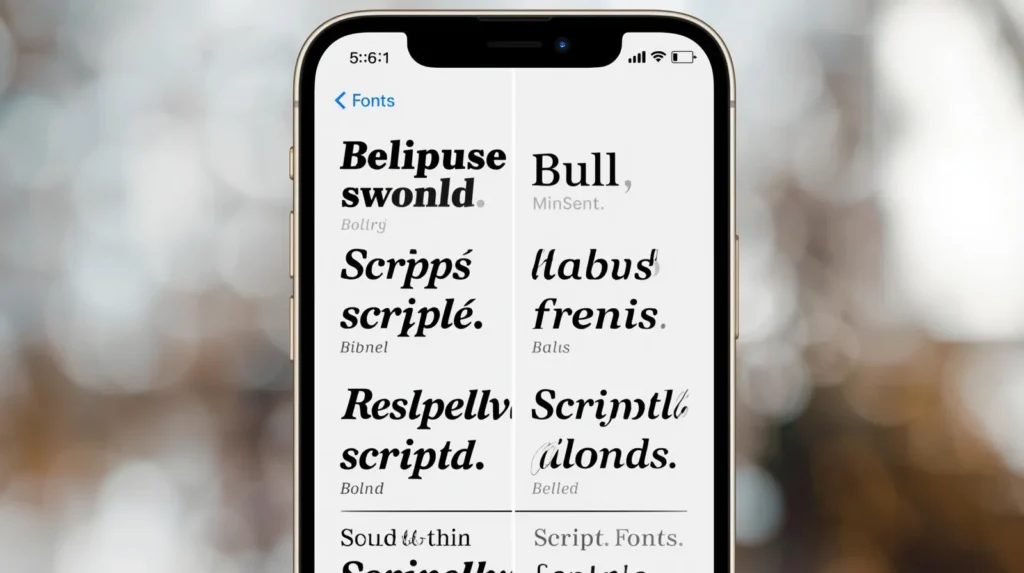
Die besten Schriftarten für Instagram Reels (nach Stil)
Klare & moderne Schriftarten
Montserrat, Helvetica und Poppins sind perfekt, wenn du Texte einfach und schnell verständlich machen willst. Sie eignen sich besonders gut für Business-Inhalte, Hooks und Überschriften, weil sie sauber und professionell wirken.
Elegante & geschwungene Schriftarten
Dancing Script, Pacifico und Allura wirken weicher und persönlicher. Diese Schriftarten passen gut zu Beauty-, Lifestyle- oder Quote-Reels, wo ein stilvoller Look wichtig ist.
Auffällige & fette Schriftarten
Impact, Arial Black und Roboto Condensed sind ideal, wenn du sofort Aufmerksamkeit willst. Sie funktionieren besonders gut für starke Aussagen, wichtige Punkte oder Call-to-Actions.
Kreative & klassische Schriftarten
Typewriter, Courier oder Instagram „Literature“ geben deinem Content einen besonderen Look. Sie passen gut zu Storytelling oder kreativen Videos, wo du etwas anders wirken möchtest.
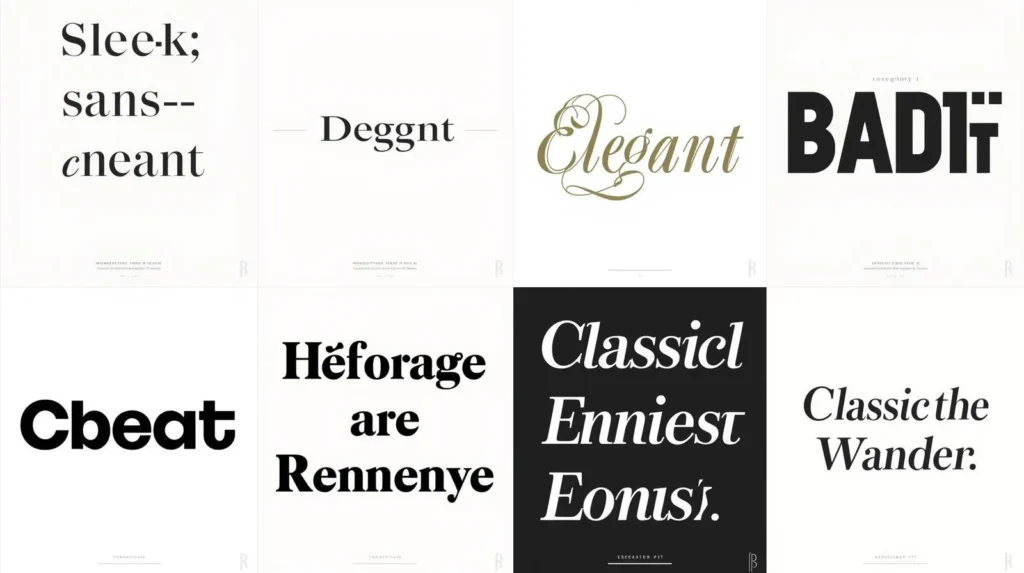
Beliebte Schriftarten auf Instagram
Laut Adobe sind die beliebtesten Schriftarten:
- Retro- und Vintage-Schriften
- Fette serifenlose Schriftarten
- Großbuchstaben (All Caps)
- Minimalistische Schriftarten
- Handschriftliche und Script-Schriften
Aber warte, sind das wirklich die beliebtesten Schriftarten? Verwende sie also nicht einfach, sondern nutze beliebte Schriftarten und recherchiere, was in deiner spezifischen Branche funktioniert. Basierend auf meiner Erfahrung habe ich recherchiert, welche Schriftart für meine Branche am besten ist. Wenn du das machst, wird es dir sehr helfen.
Zum Beispiel habe ich die Schriftarten der Tech-Branche für Instagram-Reel-Beschriftungen anhand meiner Wettbewerber recherchiert. Ich habe herausgefunden, dass die unten aufgeführten Schriftarten gut funktionieren:
- Inter
- Roboto
- Montserrat
- SF Pro (San Francisco)
- IBM Plex Mono
- Proxima Nova
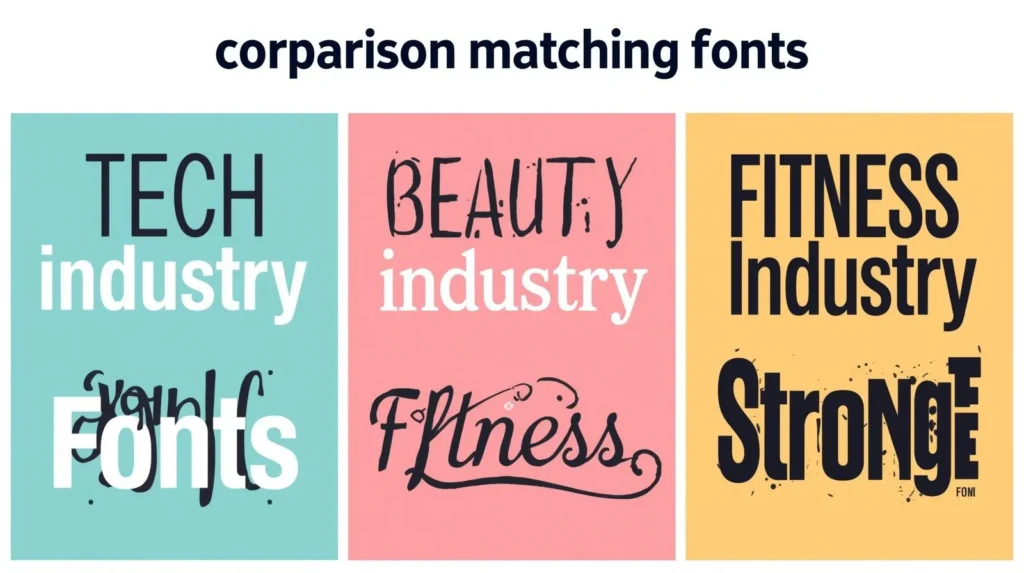
Tipps für die perfekte Schriftart
Lesbarkeit zuerst
Achte darauf, dass deine Schrift groß und klar ist. Der Text sollte sofort verständlich sein, ohne dass man genauer hinschauen muss.
Kontrast nutzen
Dein Text muss sich deutlich vom Hintergrund abheben. Wenn er schwer zu erkennen ist, springen viele Nutzer direkt weiter.
Maximal 1–2 Schriftarten
Verwende nicht zu viele verschiedene Fonts in einem Reel. Zu viel Mischung wirkt unruhig und lenkt ab.
Bleib konsistent
Nutze am besten immer ähnliche Schriftarten, damit deine Reels einen Wiedererkennungswert bekommen.
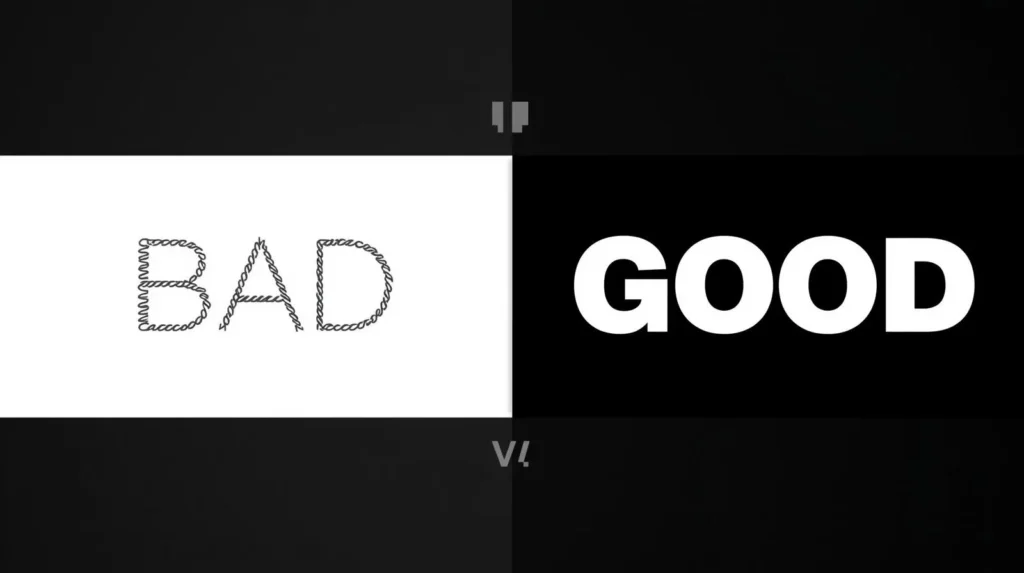
Welche Schriftarten gibt es in Instagram?
Zu den Standard-Schriften gehören Classic, Modern und Typewriter, die du direkt in der App verwenden kannst.
Fazit
Die richtige Schrift kann einen großen Unterschied machen und sorgt oft für mehr Aufmerksamkeit in deinen Reels. Halte deinen Text immer einfach, klar und gut lesbar, damit Zuschauer sofort verstehen, worum es geht. Wenn du mehr aus deinen Videos rausholen willst, kannst du zusätzlich Tools nutzen, um deine Schrift noch besser und ansprechender zu gestalten.